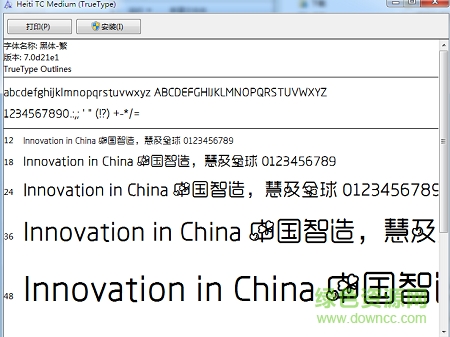
蝴蝶字體是一款非??蓯鄣闹形?a href="http://kiwanis-srv.org/k/gexingziti/" target="_blank">個性字體,該字體十分飄逸,并且還有蝴蝶圖案穿插在其中,非常彰顯了自己的個性,喜歡的朋友歡迎下載使用!
蝴蝶字體是卡通風(fēng)格的電腦字體,字體中穿插的可愛蝴蝶結(jié)極大的滿足的女人的少女心,對于平面設(shè)計來說,非常適用于廣告設(shè)計!